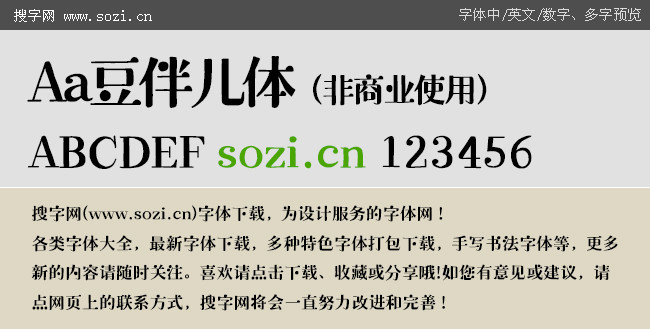
Aa豆伴兒體
搜字網(wǎng)給大家提供一款A(yù)a豆伴兒體(非商業(yè)使用)中文字體下載,該字體是一款可愛(ài)標(biāo)題藝術(shù)字體,通過(guò)對(duì)部分筆型的特殊處理,使字面空間分布更加均勻,風(fēng)格比一般的字體更有特色,連貫字跡顯得干練而不凌亂,清新簡(jiǎn)明。適合書(shū)裝設(shè)計(jì)、包裝設(shè)計(jì)、海報(bào)設(shè)計(jì)等應(yīng)用(此字體為個(gè)人非商用版,商用可以聯(lián)系QQ:1006760504)。